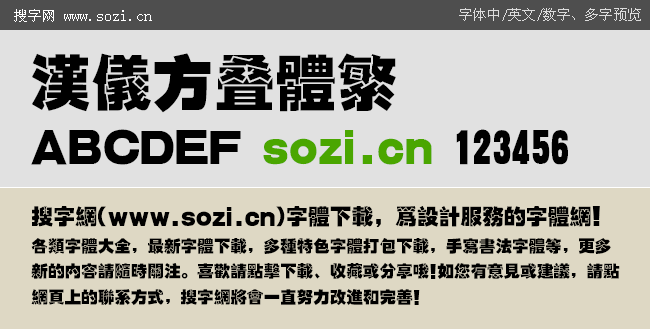
漢儀方疊體繁
漢儀方疊體繁體是搜字網(wǎng)給大家提供一款漢儀字體公司出品中文字體下載,漢儀方疊體有簡繁兩個版本,此為繁體版,這是一款很具藝術(shù)效果和設(shè)計感字體,打出來的字就像是用紙片疊起來的效果,非常好看,相信你一定會喜歡在自己作品中用到這款中文字體!繁體版雖然在設(shè)計中用途不如簡體版廣泛,但效果還是很不錯的哦,歡迎下載!